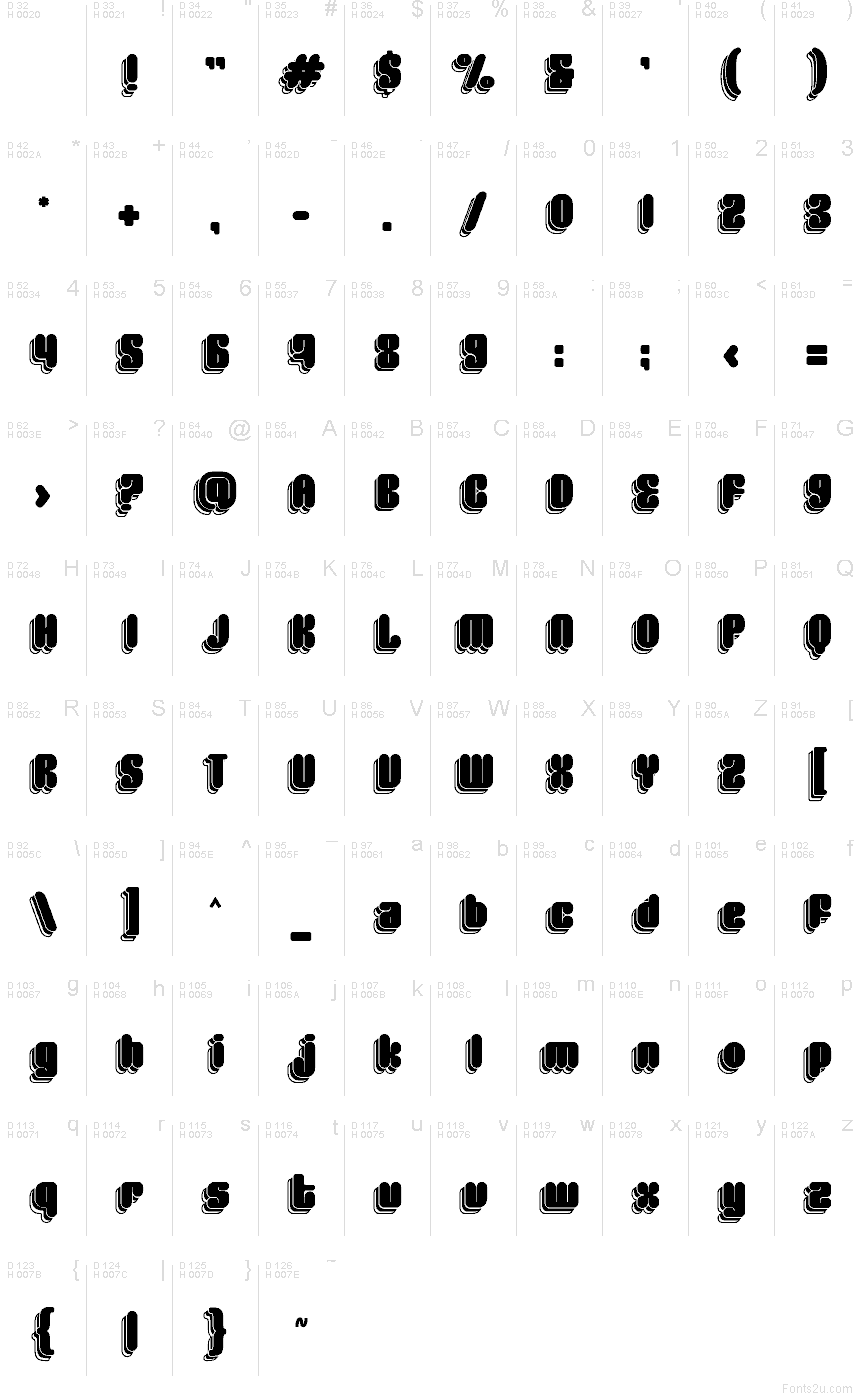
Dynamic Display Eight od Putracetol Studio je bezplatné retro 3D písmo typu display, jehož tvary vycházejí z měkkých, „nafouknutých“ siluet a pruhovaného stínu, který každému znaku dodává vzhled ručně malované reklamy. Díky zaobleným horním hranám, vtaženým křivkám a úzkým bílým zvýrazňujícím linkám působí design velmi uceleně – hloubka zde nepůsobí jako pouhý dodatečný efekt, ale jako přirozená součást písma.
Tento styl skvěle vynikne na titulcích plakátů, přebalech alb, v brandingu inspirovaném arkádovými hrami, na nálepkách či obalech, které potřebují výrazný vintage nádech, aniž by působily příliš strnule nebo mechanicky. Písmo nejlépe funguje u krátkých nadpisů a logotypů, kde vypouklý obrys a boční stín dokážou text orámovat jako skutečný grafický objekt.